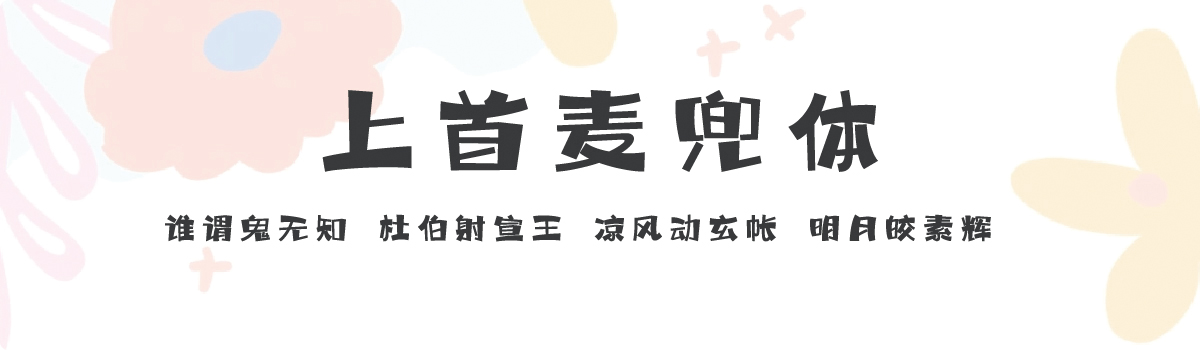
上首麦兜体
上首麦兜体,这款字体结构工整、笔画清晰,兼顾美观与易读性,适用于标题、正文、海报、包装、LOGO 等多种场景。字形优雅稳定,风格百搭耐看,适配日常排版与创意设计,让文字呈现更舒适、更具质感。上首麦兜体一笔一画,皆是细节,以均衡的比例、流畅的线条打造舒适视觉体验,字形端正大气,风格简约现代。无论是商业设计、品牌宣传还是日常排版,都能轻松驾驭,让文字更有格调与力量。上首麦兜体字体下载。